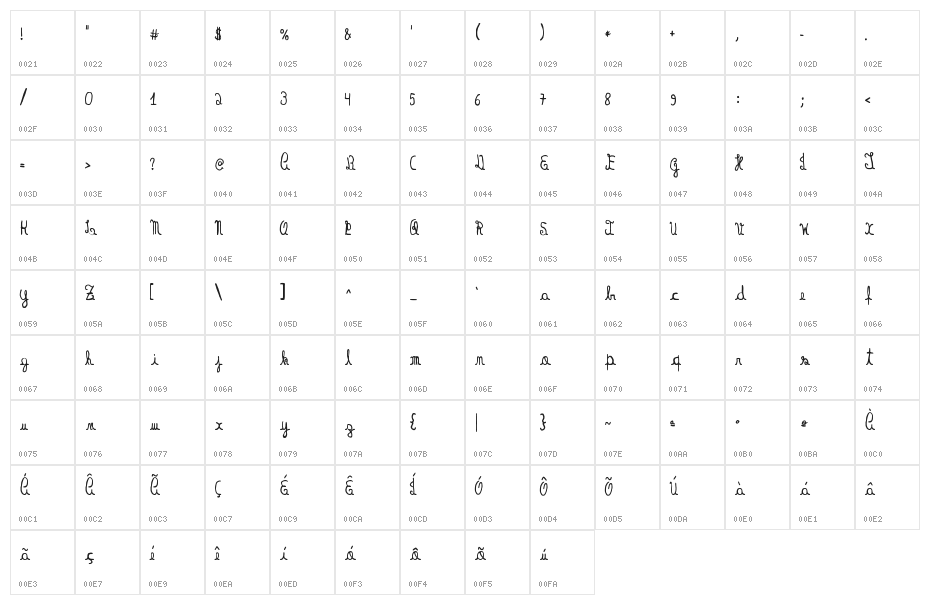
Handrey Sans Font
| Anwendungsfall | Logos, Invitations, Creative projects |
| Vorgeschlagene Projekte | Ideal for greeting cards, invitations, personal branding, and creative projects that require a unique, personal touch. |